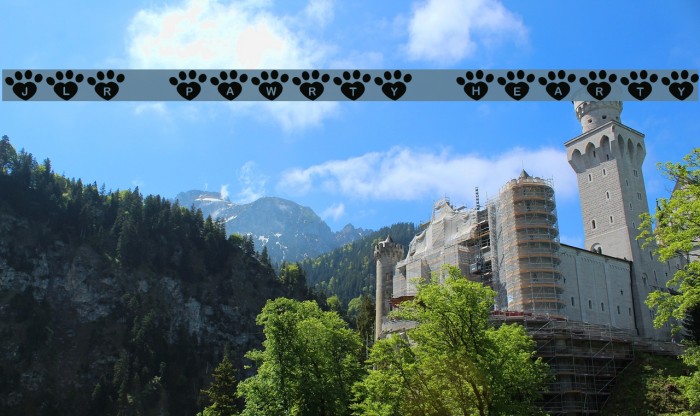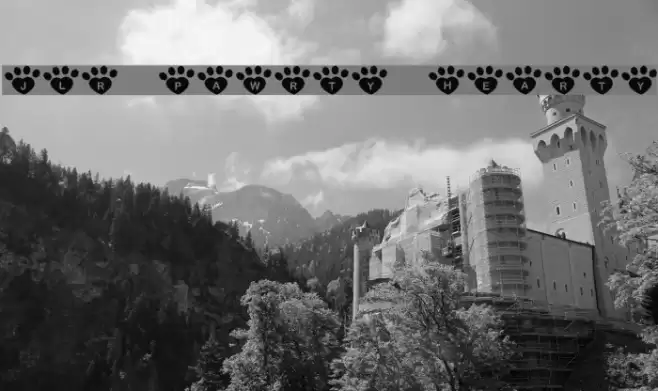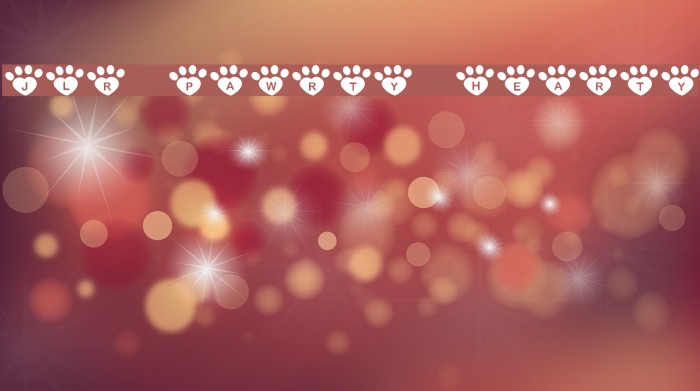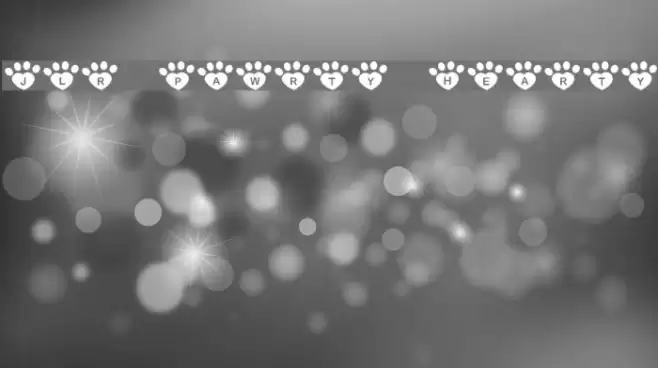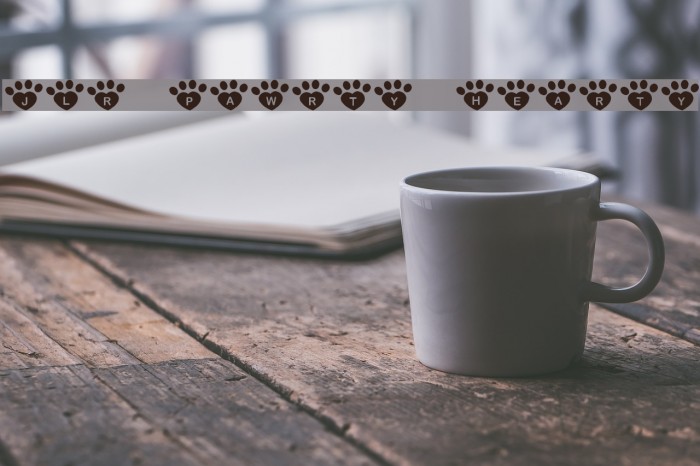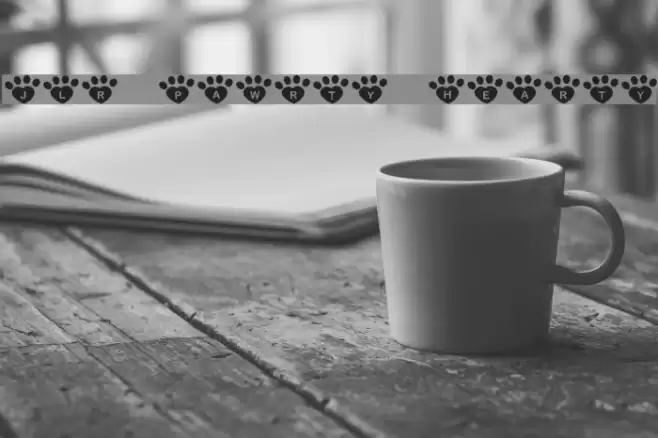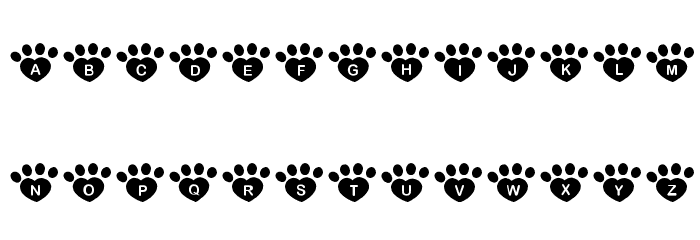
JLR Pawrty Hearty Font
| समग्र शैली | Decorative |
| उपयोग का मामला | Logos, Headlines, Posters |
| सुझाए गए प्रोजेक्ट | Ideal for pet store branding, children's books, playful posters, and animal-themed events. |